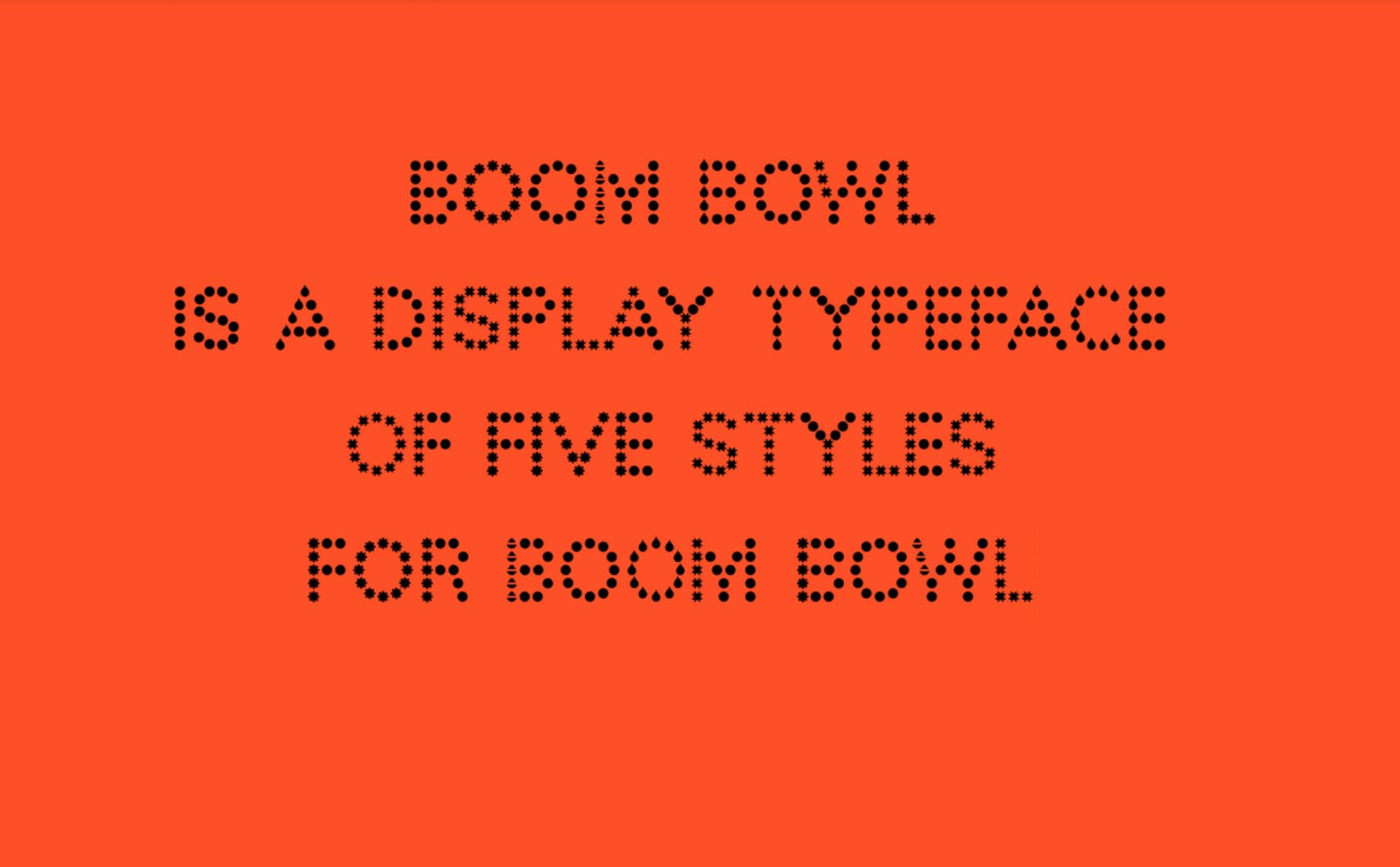
El Cliente: Boom Bowl es un restaurante take-out de Poke con una personalidad amigable.
El Objetivo: Crear una marca diferenciándose de competidores a través de su personalidad atractiva y amigable.
La Solución: La identidad para este proyecto, esta basada en la representación visual de la cultura de mezcla de ingredientes, de la mano con la practicalidad y personalización del poke. Creamos una tipografía dinámica basada en Lab Grotesque de Letters From Sweden con un sistema basado en puntos que incluye cuatro iconos funcionando individualmente y representando los componentes que conforman al platillo: base, proteína, toppings, y aderezos. Los elementos de la cara de los iconos se diseñaron empatando con los puntos de la tipografía. El logotipo resultante genera variantes reclamando las ventajas de su versatilidad tipográfica.